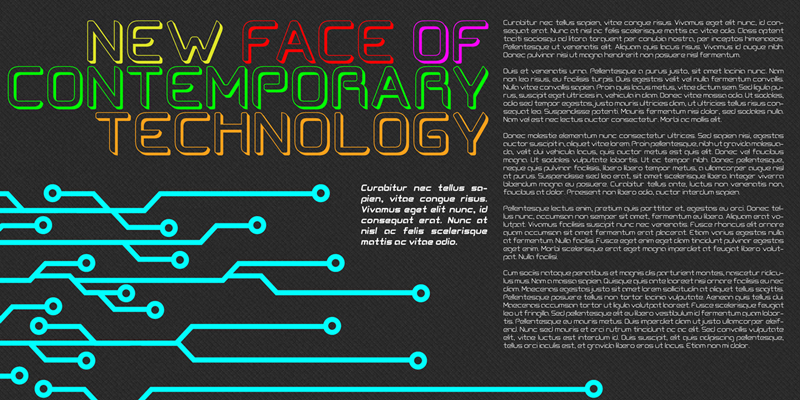
Preview and download Cogtan Font. Created by Lerima in Techno Various styles with 100% Free license.
Cogtan Shadow é uma versão reduzida da família Cogtan; Cogtan é uma fonte de forma geométrica, com estrutura única. A forma de cada glifo é muito simples e contemporânea. Eu recomendo usar em título ou frase curta em cartazes e especialmente úteis para o trabalho de design. Você pode ver minhas outras fontes nos sites abaixo: http://www.fontspring.com/foundry/leandro-ribeiro-machado?refby=lerima http://www.hellofont.com/fonts/1166?a=TY http://www.hypefortype.com/foundries/leandro-ribeiro-machado.html https://www.behance.net/leandro_ribeiro |